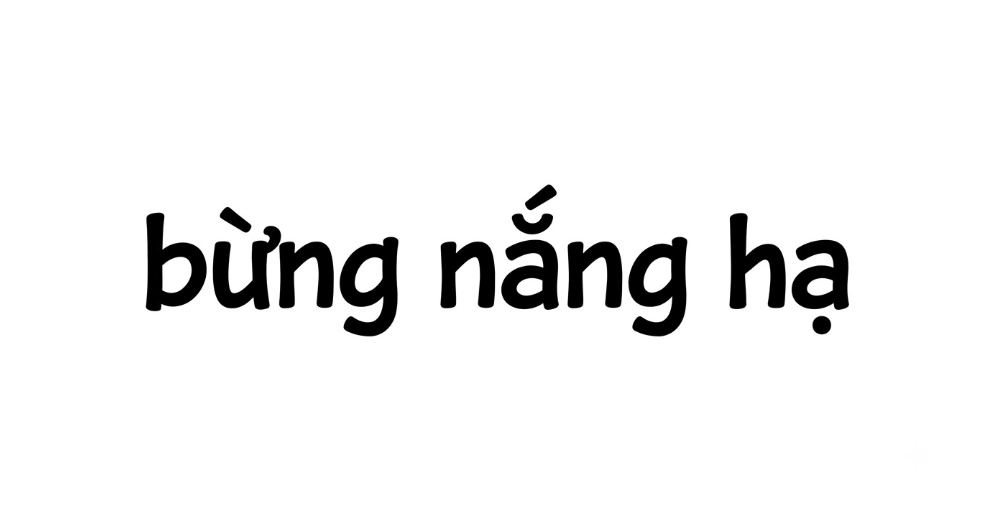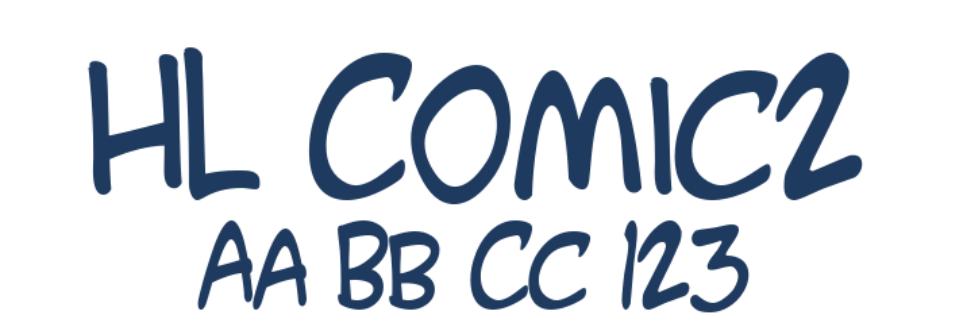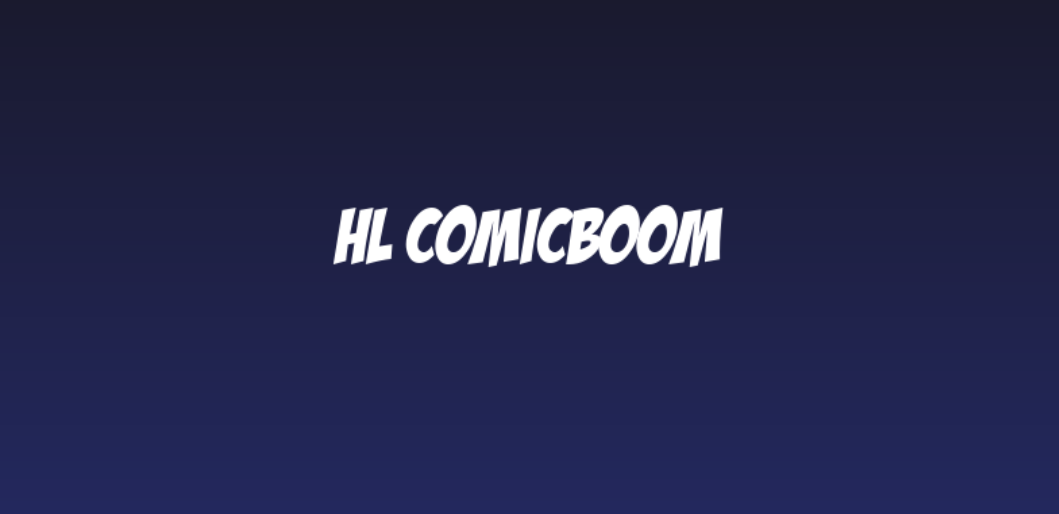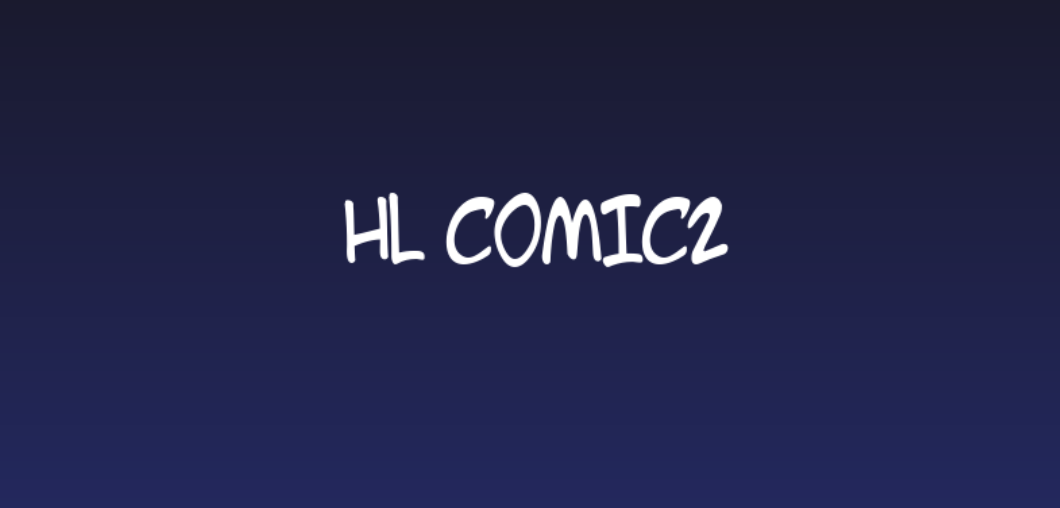
Đặc điểm thẩm mỹ độc đáo của bộ font HL Comic
Font HL Comic không đi theo sự cứng nhắc của các phông chữ hình học; nó mang đến một ngôn ngữ thị giác đầy tính biểu cảm, tái hiện trọn vẹn sự vui tươi của nghệ thuật hoạt hình.
Phong cách truyện tranh vui nhộn và thân thiện
Đặc trưng lớn nhất của Font HL Comic Việt hóa là cấu trúc chữ mô phỏng lại những nét bút lông hoặc bút dạ vẽ tay trong các khung truyện tranh thiếu nhi. Nét chữ có độ dày dặn vừa phải, các đường nét hơi xiêu vẹo tự nhiên tạo nên một nhịp điệu Typography vô cùng sinh động. Khi đặt phông chữ này làm tiêu đề trên bao bì, sản phẩm của bạn sẽ ngay lập tức lan tỏa cảm xúc vui vẻ, kích thích sự tò mò của các bạn nhỏ cũng như các bạn trẻ năng động.
Cấu trúc chữ rõ nét tối ưu cho bong bóng hội thoại
Các ký tự trong Font HL Việt hóa sở hữu tỷ lệ x-height rộng rãi cùng khoảng hở trong chữ (counter) thoáng đãng. Thiết kế này giúp phông chữ duy trì độ dễ đọc (legibility) xuất sắc ngay cả khi in ở kích thước siêu nhỏ trên tem nhãn hoặc khi đặt trong các ô hội thoại chật hẹp, giúp người xem tiếp nhận thông điệp một cách nhanh chóng.
Ưu điểm nổi bật của bản Font HL Việt hóa
Khi ứng dụng các phông chữ truyện tranh vào thị trường trong nước, sự chỉn chu về dấu câu là yếu tố quyết định đến tính chuyên nghiệp của ấn phẩm:
- Khắc phục triệt để lỗi dấu tiếng Việt: Phiên bản Việt hóa đã được đội ngũ thiết kế trau chuốt thủ công từng dấu câu. Các dấu sắc, huyền, hỏi, ngã, nặng được vẽ với tỷ lệ cân đối, đặt ở vị trí thoáng đãng so với thân chữ, không gây cảm giác chắp vá hay đè nét làm mất tính thẩm mỹ.